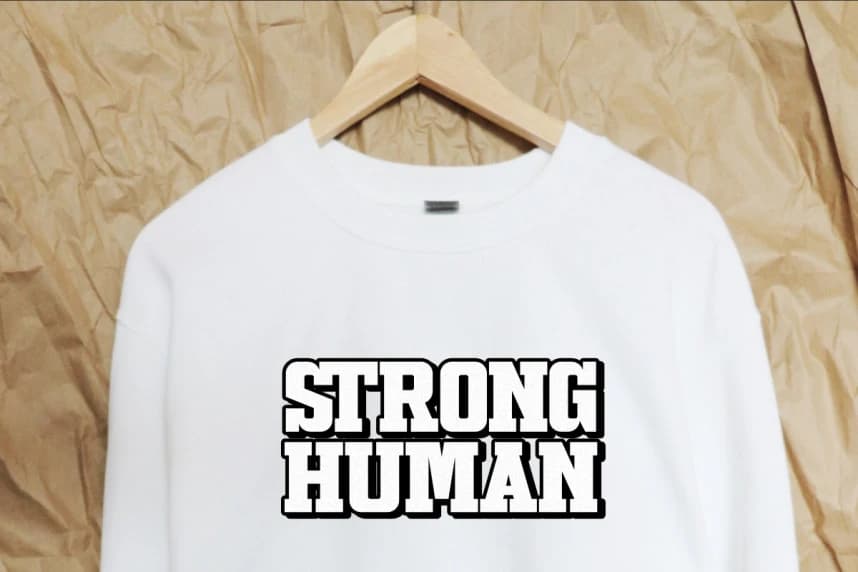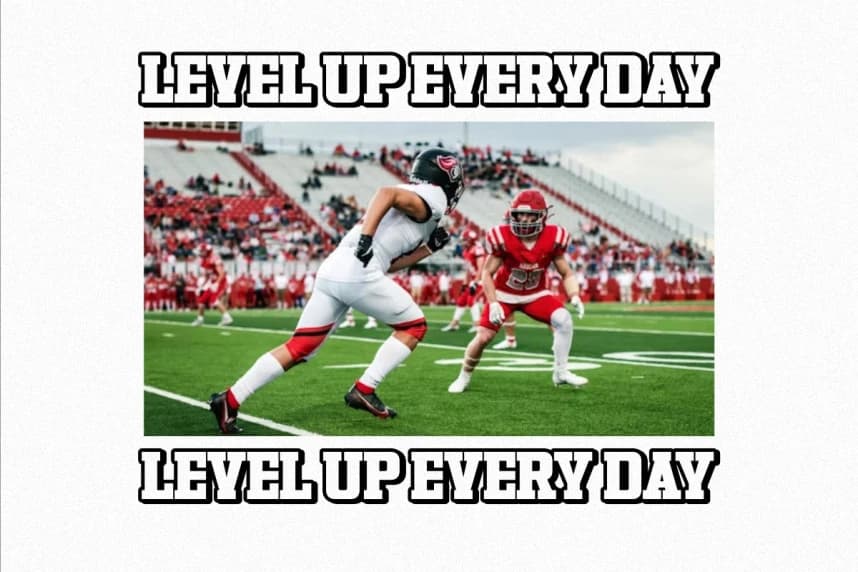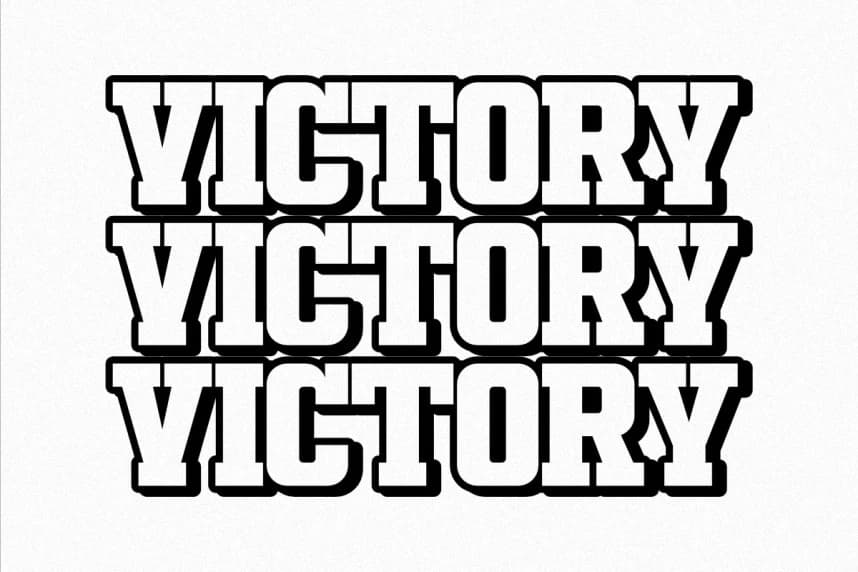
Black Spirit Font gerçekten devasa ve son derece güçlü bir Condensed Display Typeface'tır. Ultra kalın, blok benzeri bir yapıya sahip olan bu yazı tipi, temiz hatlar ve pürüzsüz yuvarlatılmış köşelerle karakterizedir ve retro bir vurucu etkiyi şık bir modern çekicilikle kusursuzca birleştirir.
Black Spirit Font gerçekten muazzam ve inanılmaz güçlü bir Sıkıştırılmış Gösterim Yazı Tipi. Temiz hatlara sahip, pürüzsüz yuvarlatılmış köşelerle karakterize edilen ultra kalın, blok benzeri bir yapıya sahiptir ve retro bir vurgu ile şık modern bir çekiciliği mükemmel bir şekilde dengeler.